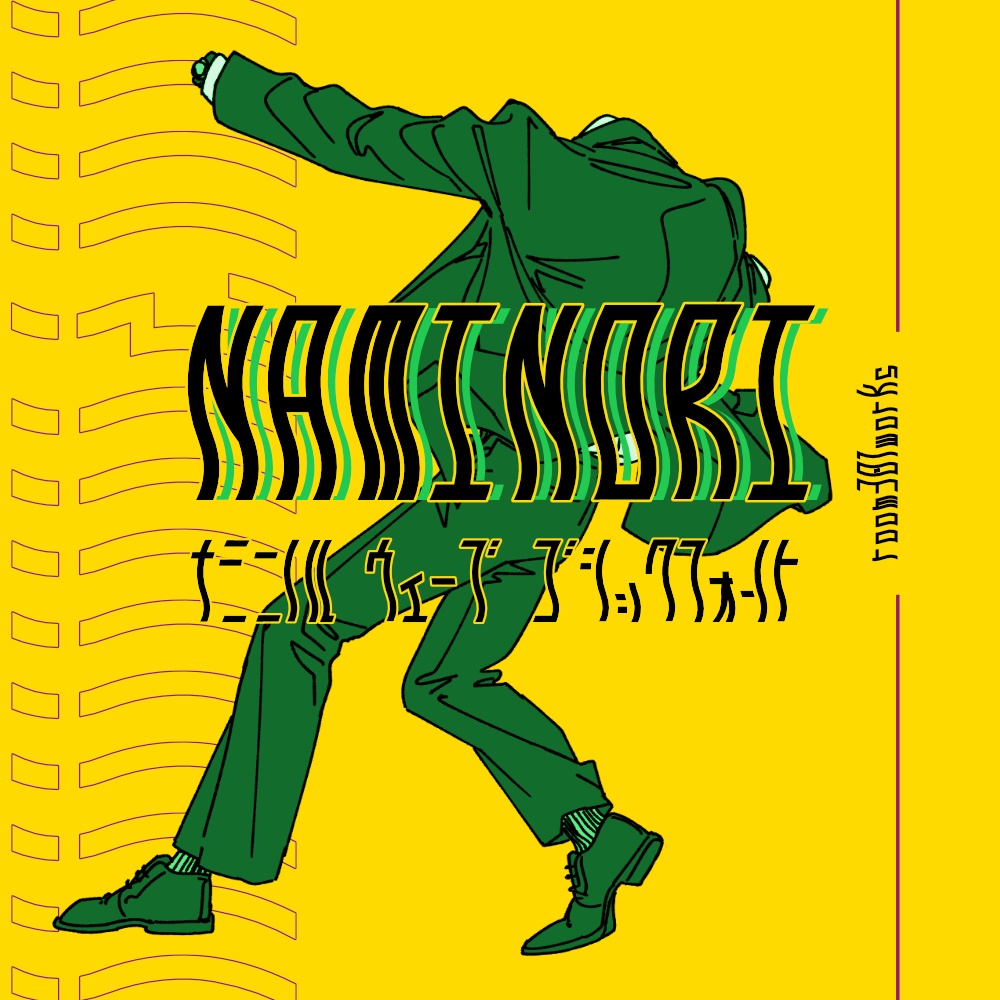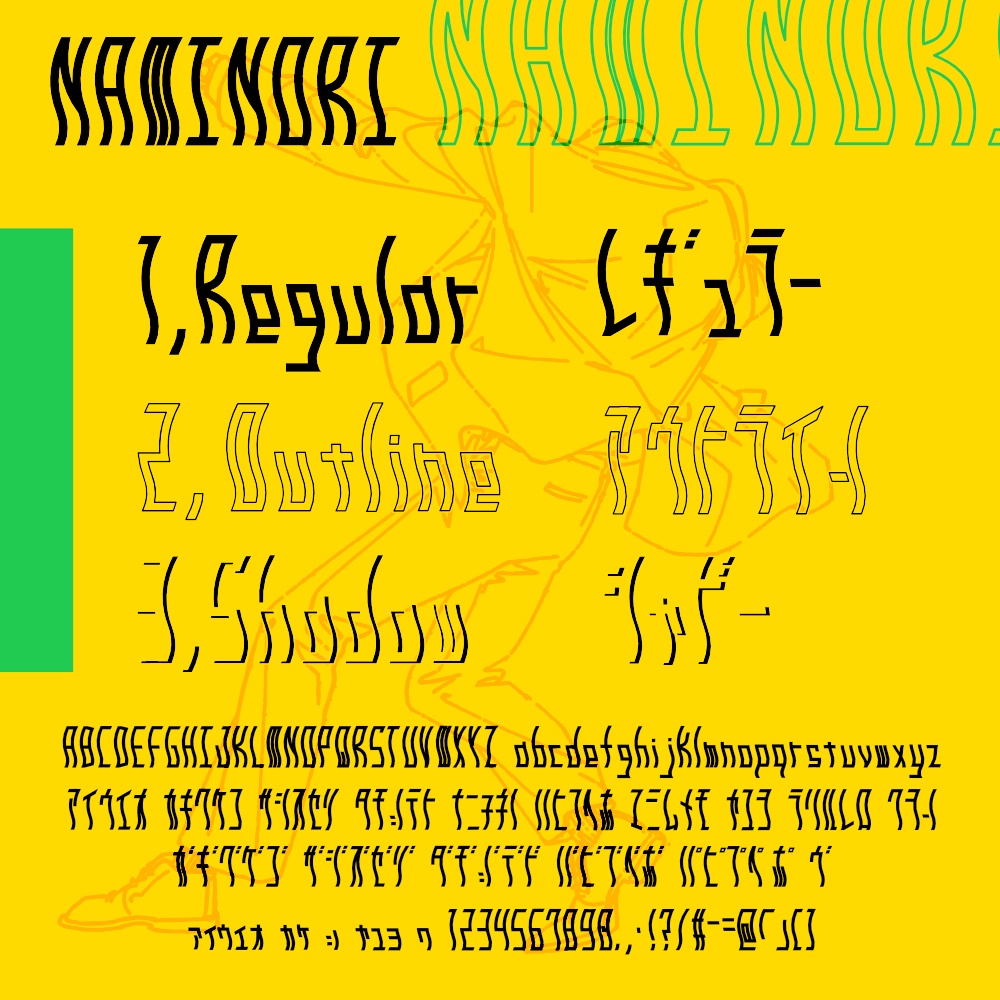
【フォント】NAMINORI
【NAMINORI】 英数字とカタカナで構成された、ウェーブ感のあるゴシックフォントです。 収録内容 フォントデータ:3スタイル ・通常(黒文字) ・袋文字(アウトライン) ・影文字 対応文字 ・英数字(大文字・小文字) ・カタカナ ・記号(一部) ・濁点文字(一部) ※対応文字は商品画像をご確認ください。 動作確認 ・Windows 11 環境にて動作確認済み 対応環境について ・OpenType(.otf)/TrueType(.ttf)形式のため、 Mac環境でも一般的なフォント対応ソフトでは使用可能と考えられますが、Macでの実機確認は行っておりません。 環境差による表示の違いが出る可能性があります。あらかじめご了承ください。 利用範囲 ・個人利用:OK ・商用利用:OK(クレジット表記不要) NG事項 ・フォントデータ自体の再配布・転売 ・フォントデータの改変配布 ・商標登録・ロゴ登録目的での使用 注意事項・免責事項 ・本フォントは手作業で制作しているため、文字の揺らぎや個体差があります。 フォントの風合いとしてお楽しみください。 ・使用環境やソフトウェアによって、表示が異なる場合があります。 ・本フォントの使用によって生じたいかなる不具合・損害についても、制作者は責任を負いかねます。あらかじめご了承ください。 ※不具合等がありましたら、BOOTHメッセージよりご連絡ください。